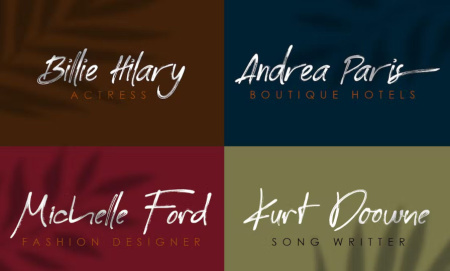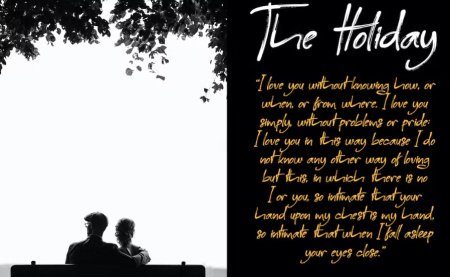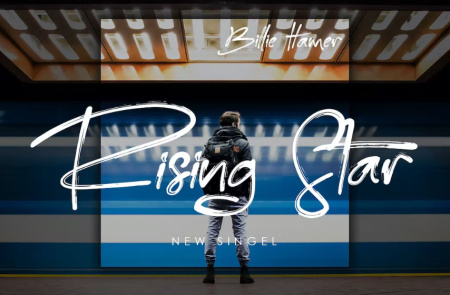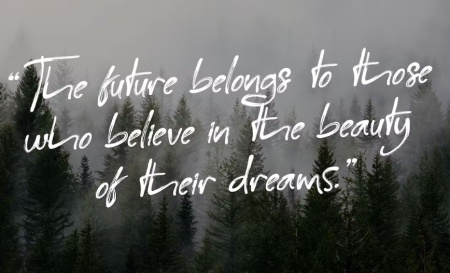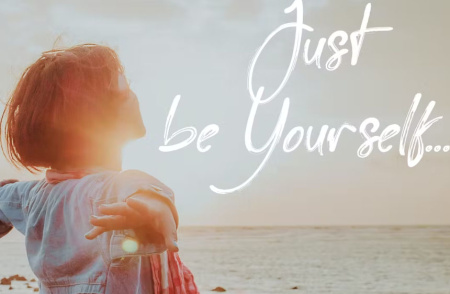
دانلود فونت دستخط انگلیسی Reingttoon
دانلود فونت دستخط انگلیسی Reingttoon از سایت gfx یک فونت دستخط انگلیسی با طراحی زیبا و مدرن است. این فونت دست نویس انگلیسی برای طراحی پوستر، جلد کتاب، کالا، کمپین‌های مد، خبرنامه، برندسازی، تبلیغات، مجلات، کارت‌های تبریک، جلد آلبوم، و طرح‌های نقل قول و موارد دیگر عالی است.